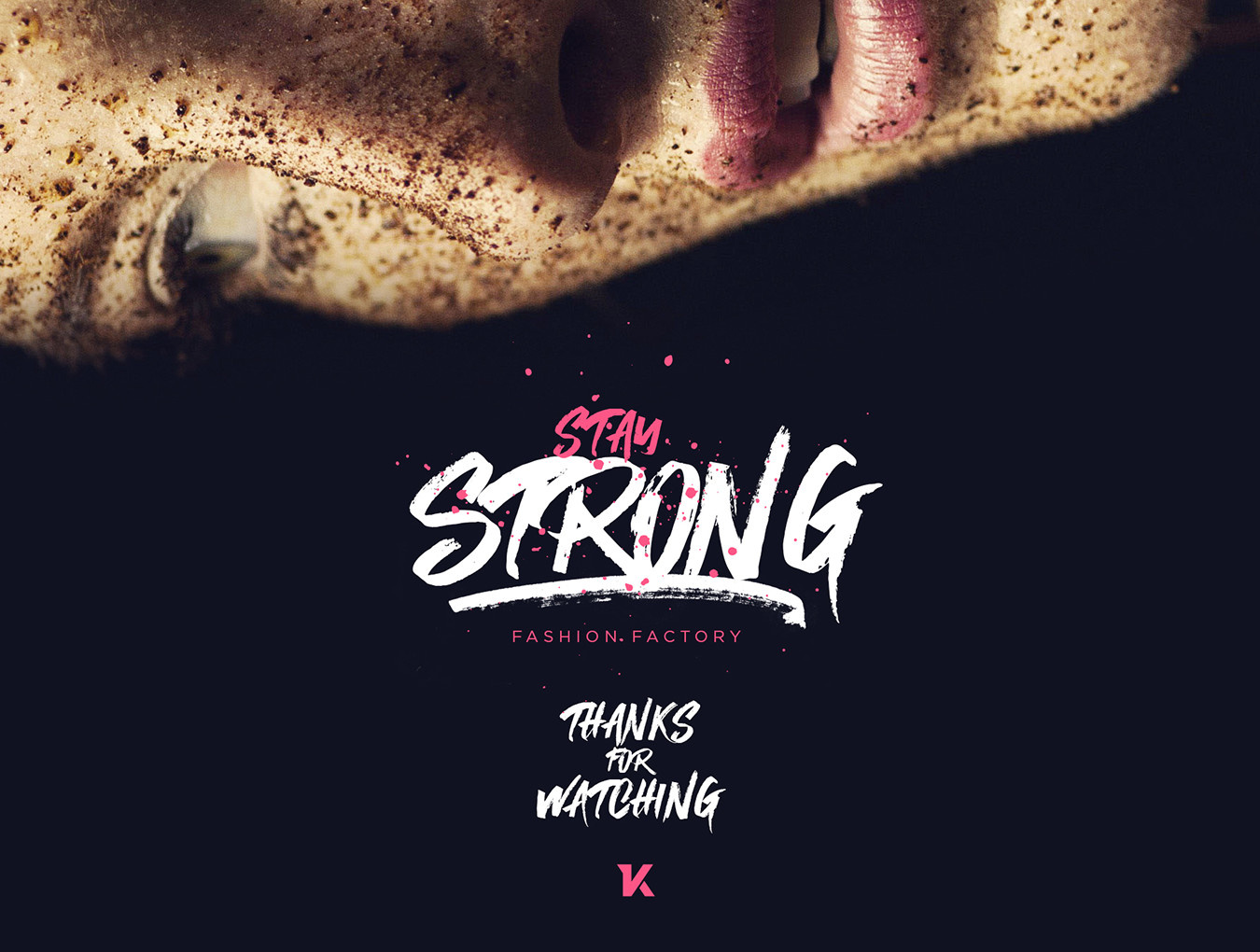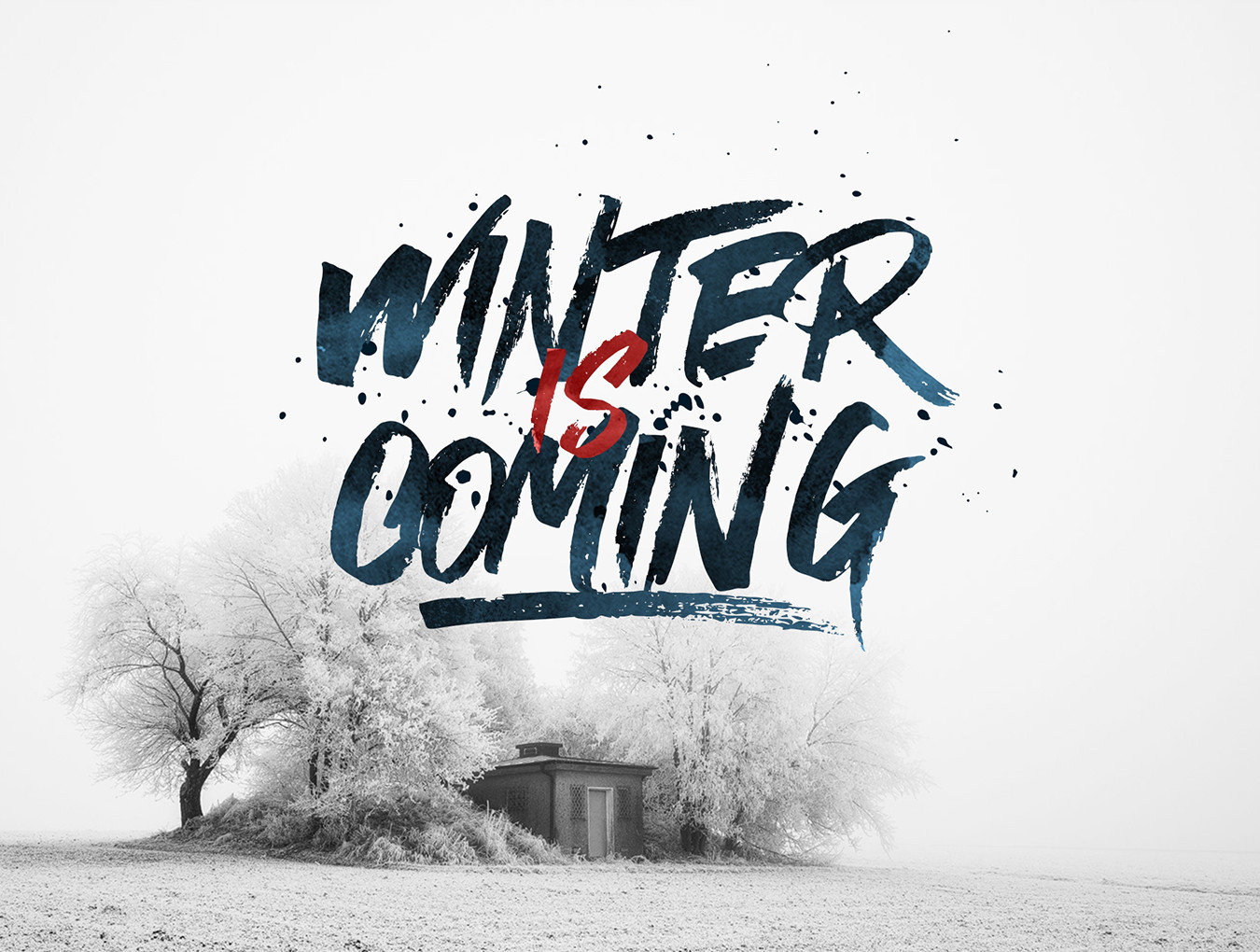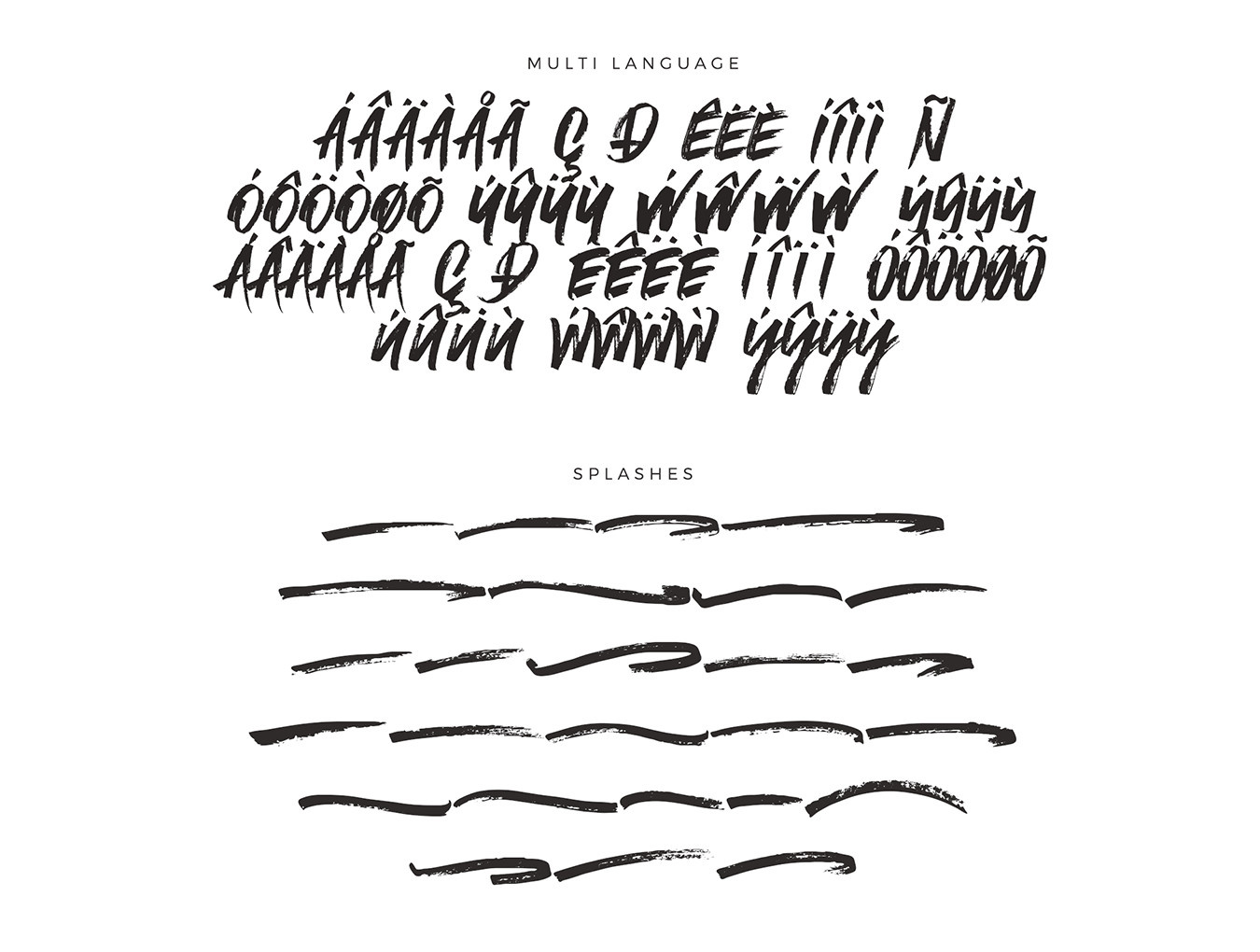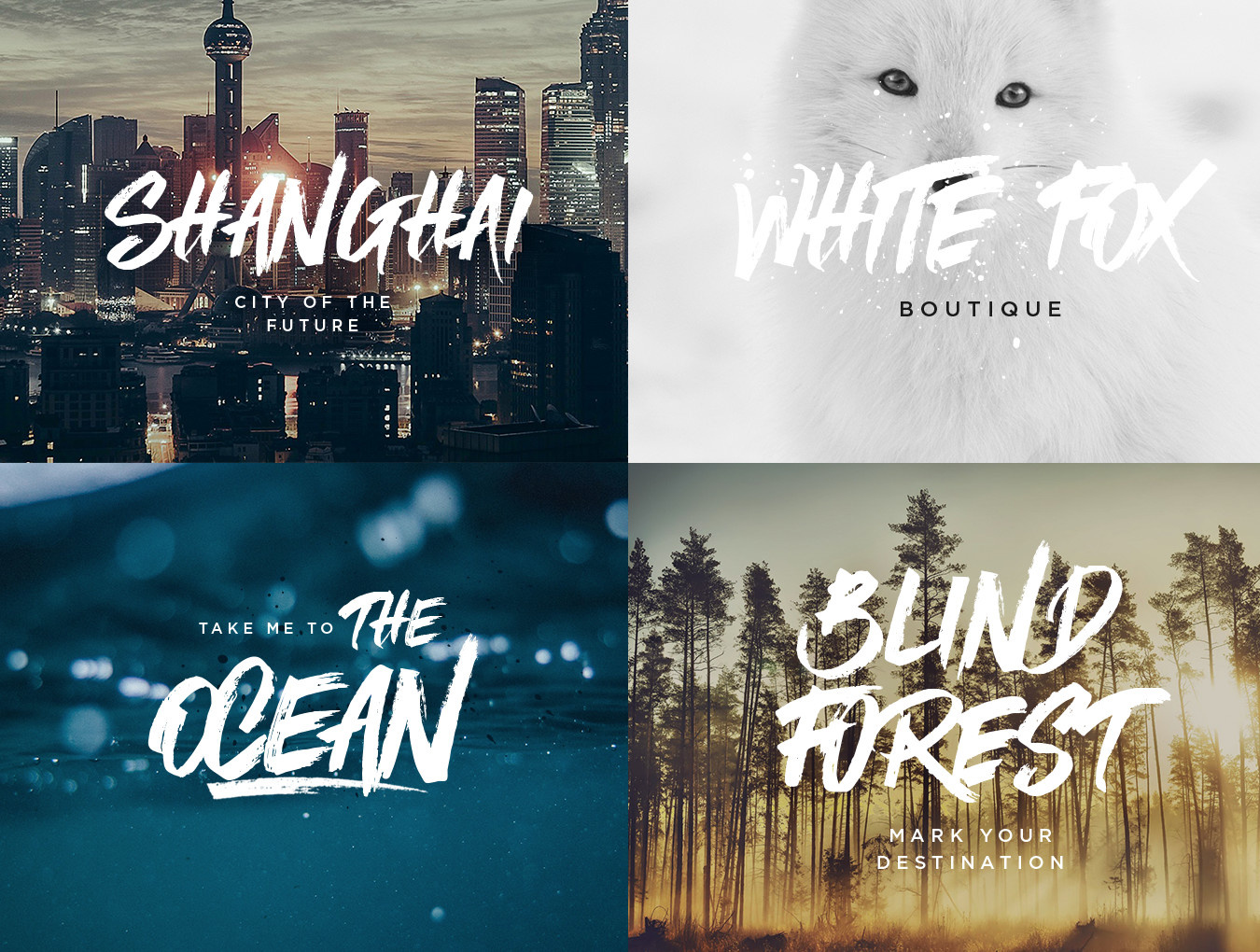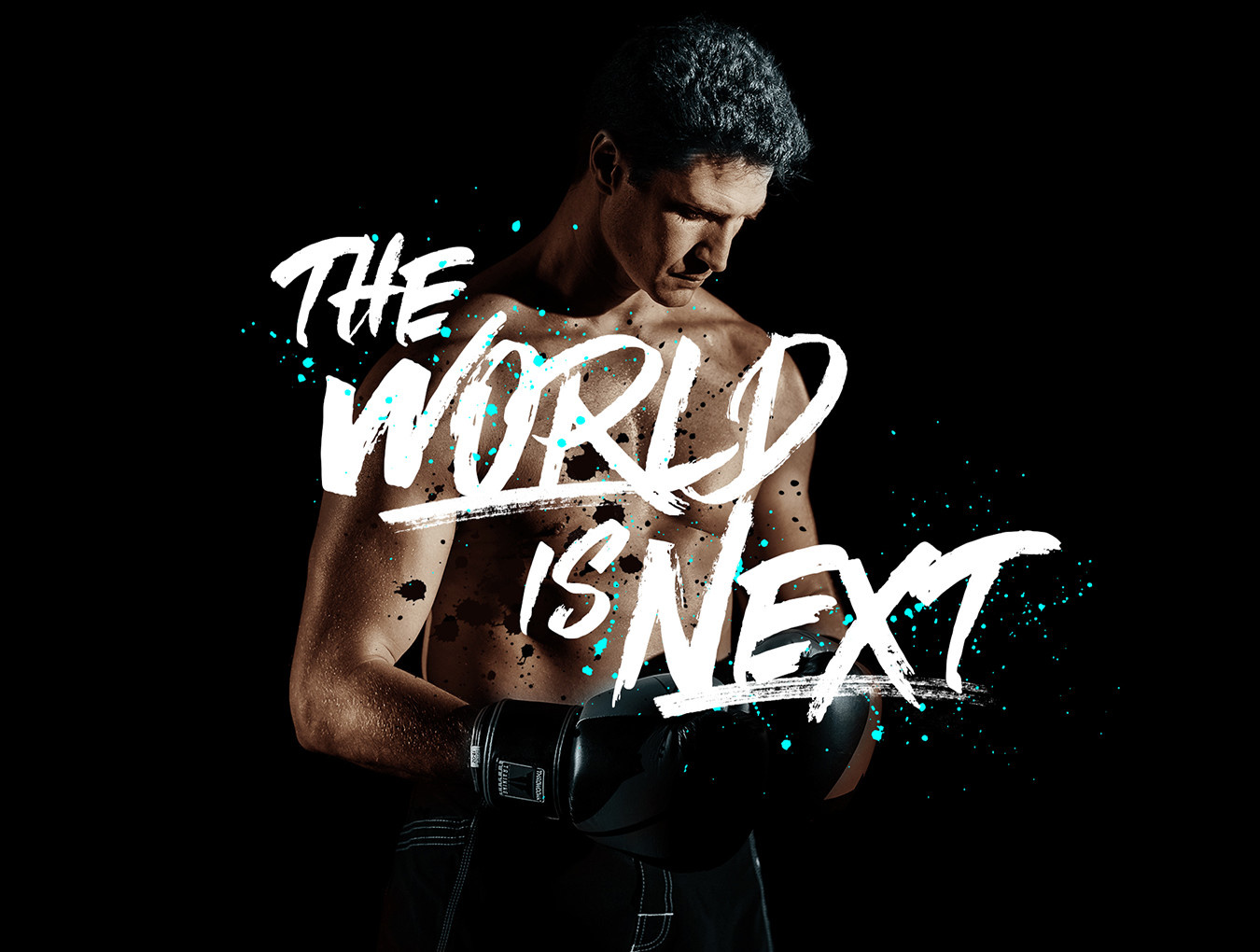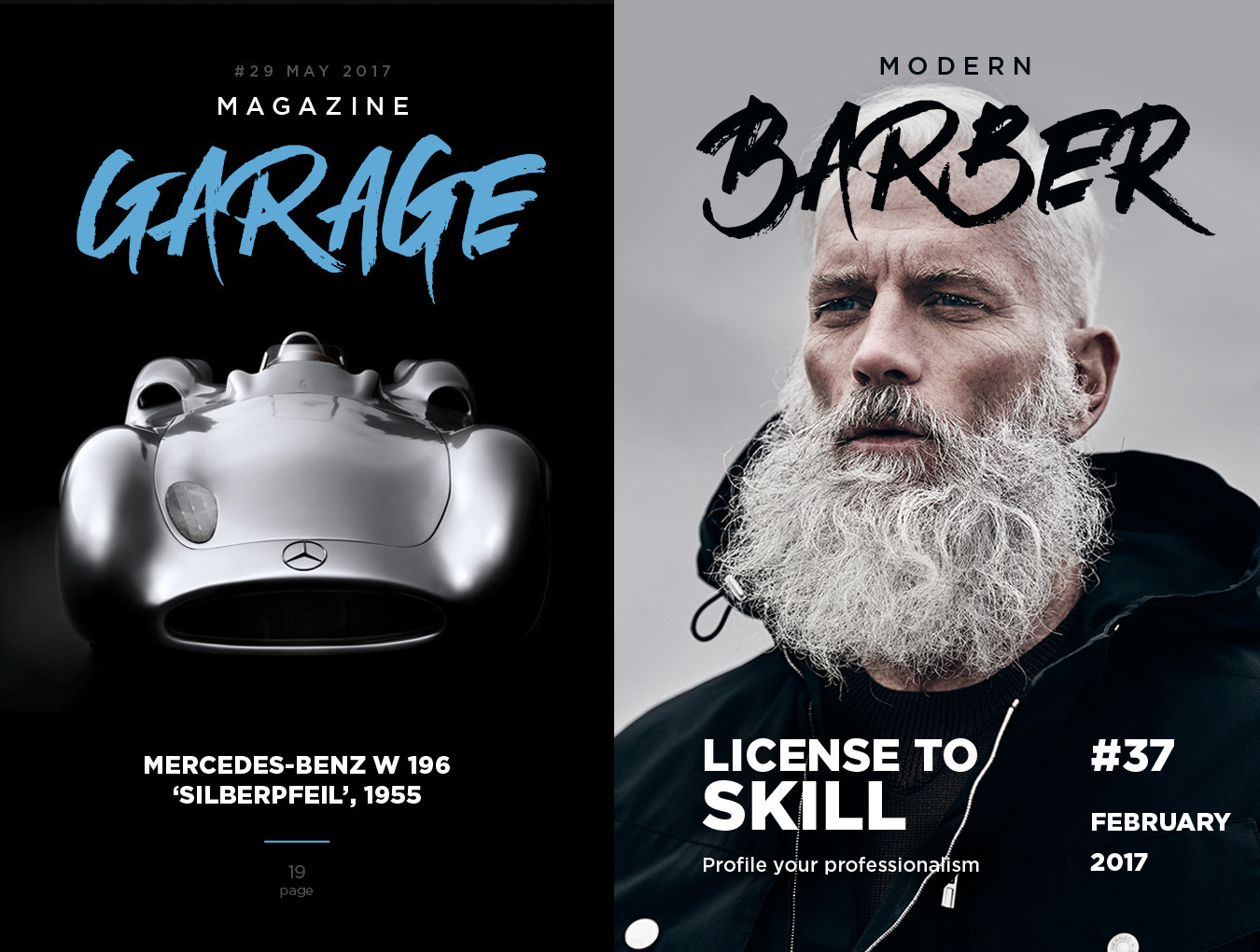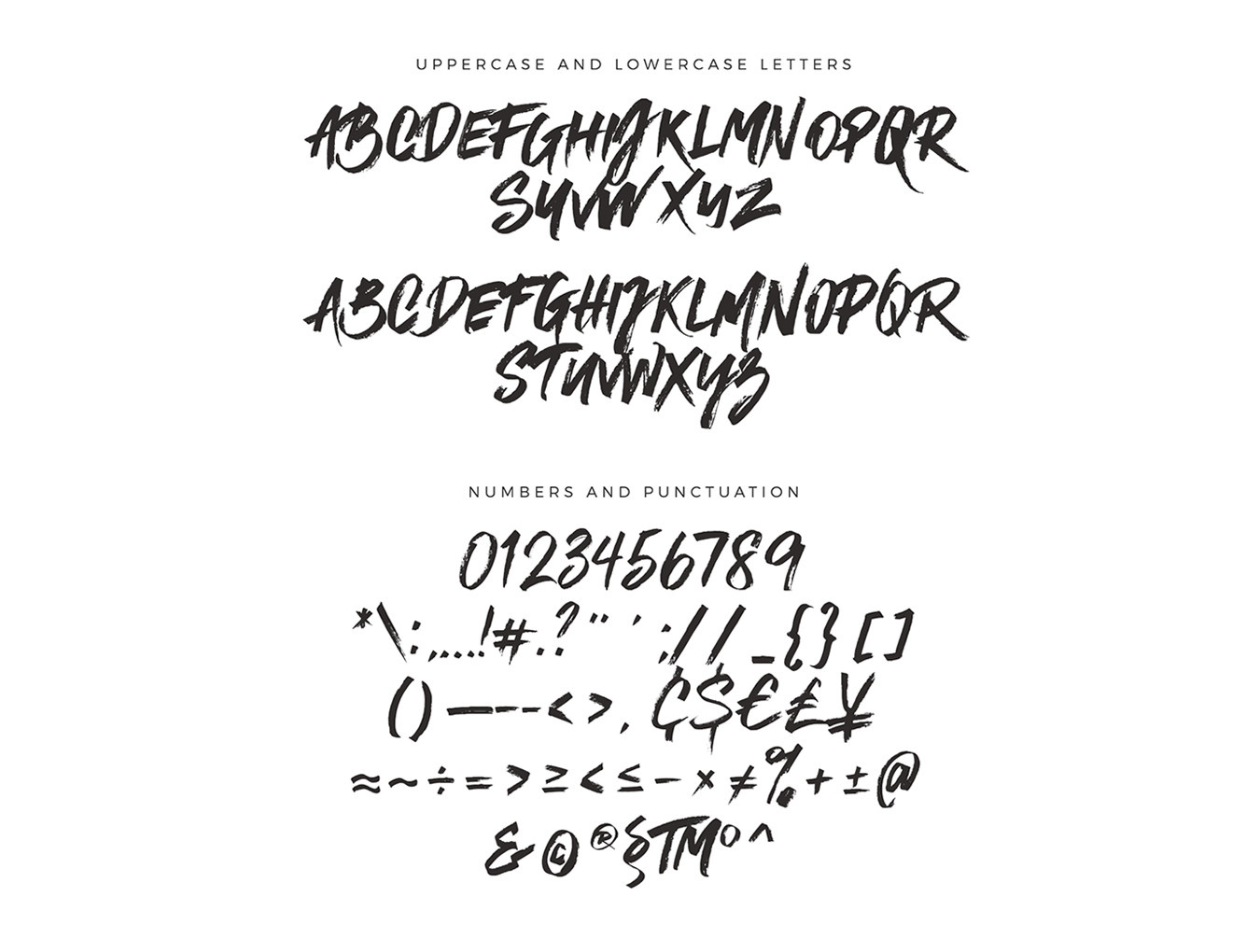
适合一切的完美标记字体!,Mystique Marker字体
Perfect Marker Font for everything!, Mystique Marker Font
Mystique带有一整套大小写字符 - 让您更自由地将文字转换为真正的定制手工字母。 Mystique字体包括大量字形,包括数字,标点符号和多语言支持。